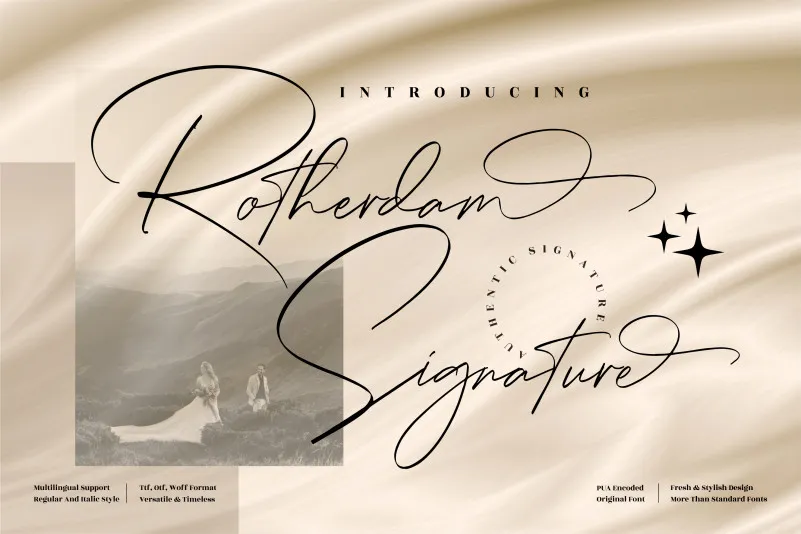
Rotherdam Signature Font – Download Grátis
Essa é uma fonte de assinatura premium perfeitamente adequada para diversos projetos criativos, desde identidades visuais, projetos de marca até designs de embalagens e materiais de publicidade. Seja ela a escolha ideal para seus logos pessoais, rótulos em produtos, cartões de visita ou mesmo capas de livros. A Rotherdam Signature Font é uma opção perfeita para aqueles que buscam adicionar um toque especial aos seus trabalhos e dar um brilho premium à sua criação. Seja ela a assinatura ideal que você precisa para tornar seu design único, elegante e de alto padrão. Além disso, essa fonte é perfeita para projetos personalizados e de luxo como cartões de convite, cartazes promocionais ou até mesmo materiais comemorativos. Ela pode ser usada em tudo o que você desejar dar um toque personalizado a partir dos mais simples até os mais elaborados projetos. Com uma grande variedade de opções de estilo e facilidade de uso na sua interface, a Rotherdam Signature Font é sem dúvida uma ótima escolha para quem busca qualidade no seu trabalho gráfico.